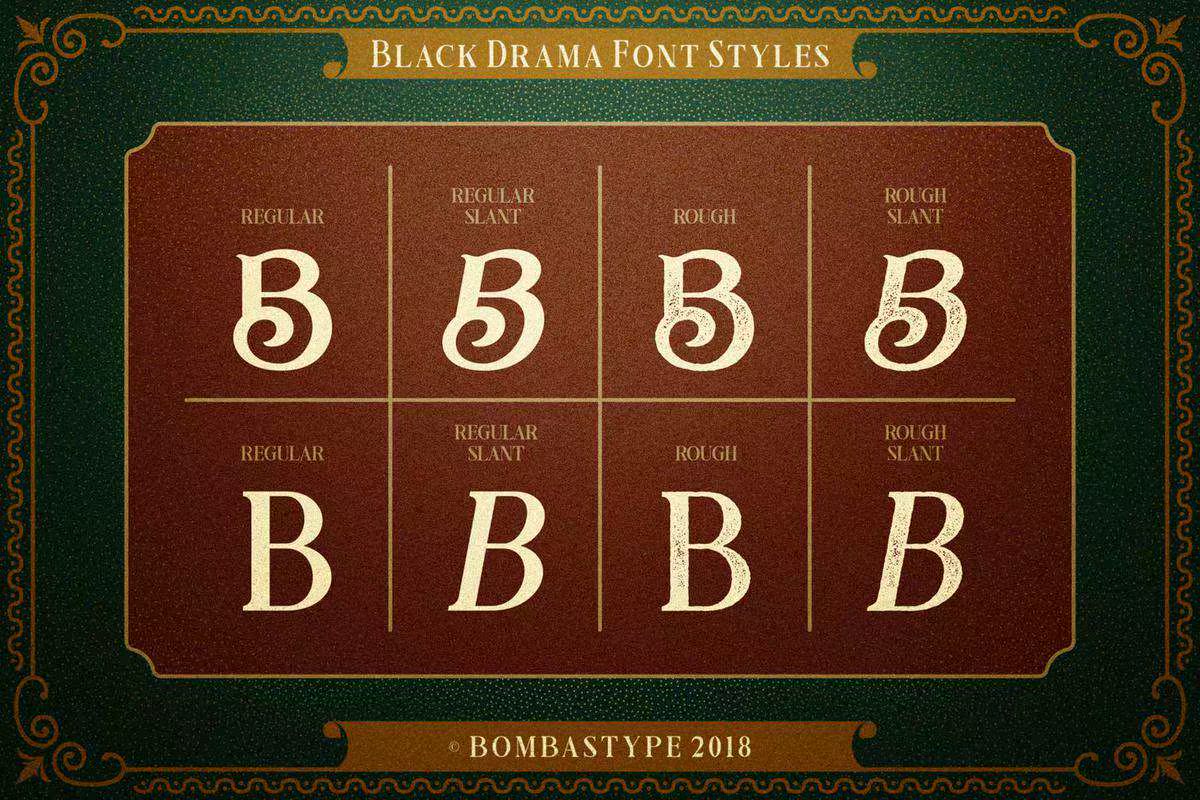
一个完整的三角帆和三角帆的组合。它包含两个清晰、粗糙、规则和倾斜版本的展示系列。三角帆以华丽的形状元素展示系列。它还包括许多交叉韧带、韧带和任意韧带。第二个三角帆是三角帆,带框架,FloralElement和插图是一种完美的组合。这种字体组合非常适合您的许多设计项目。例如:荧光灯、标志设计、徽章、包装、邀请等等。Abeautifula和LegaantFontCombination。它包含2种简洁、粗糙的展示风格,这两种字体的常规和倾斜版本。主字体显示的是一系列丰富的形状元素。它还包括许多可选的标签、连字带和任意连字带。第二种字体是带有边框、花卉元素和插图的完整组合。这种字体组合非常适合您的许多设计项目。如标签、标志设计、徽章、包装、,邀请赛等等。